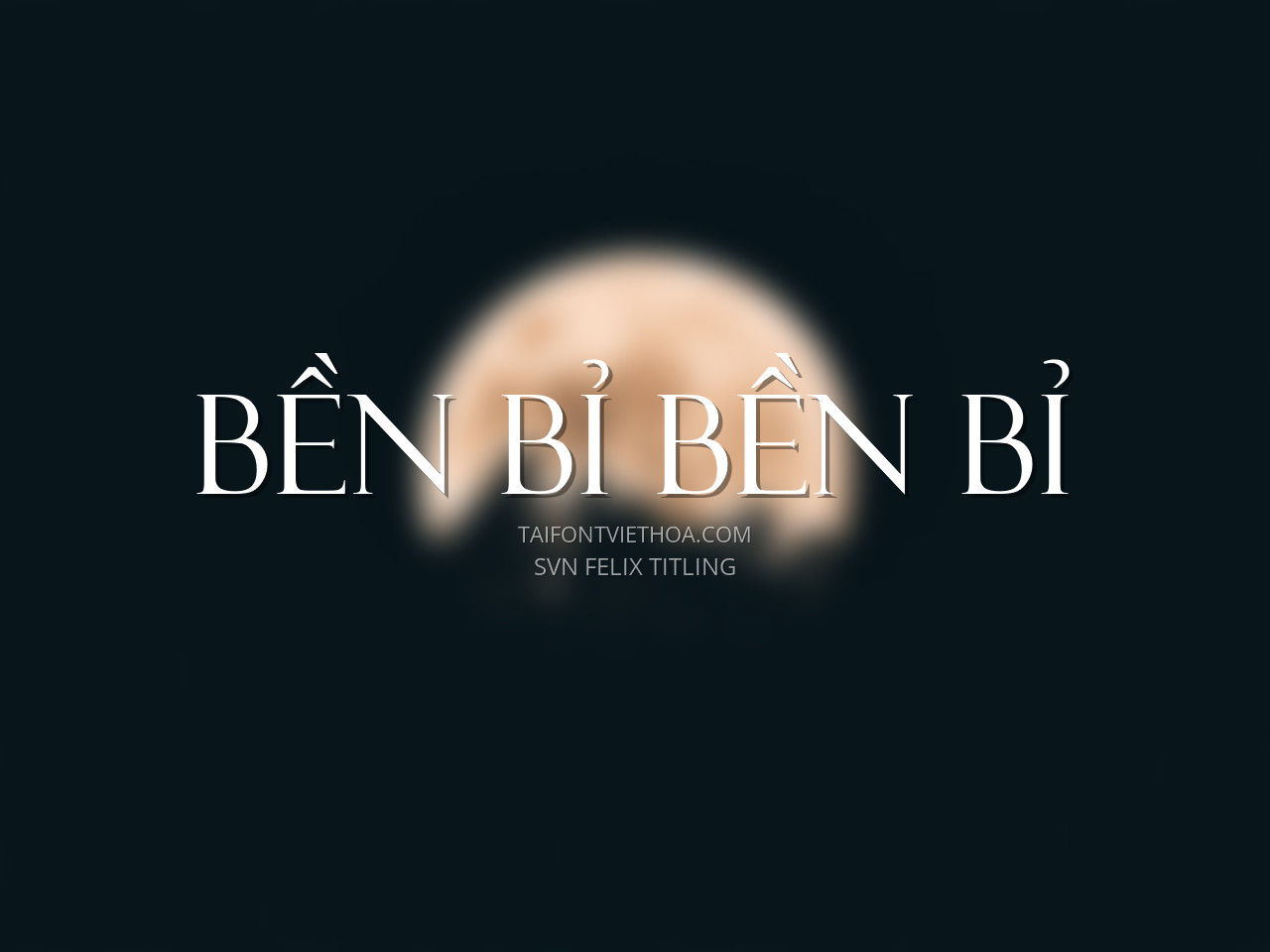
Font việt hóa SVN Felix Titling
Tác giả Font: Phillip Boydell
Giới thiệu về font SVN Felix Titling – Kiểu chữ serif in hoa cổ điển, trang trọng và sắc nét
SVN Felix Titling là phiên bản Việt hóa của font Felix Titling – một kiểu chữ serif chỉ bao gồm chữ in hoa với thiết kế cổ điển, thanh lịch và sắc nét. Font được tạo ra nhằm mang lại sự trang trọng và chuyên nghiệp, rất phù hợp cho các dự án thiết kế tiêu đề, logo, bảng hiệu và các ấn phẩm cao cấp.
Phiên bản Việt hóa của SVN Felix Titling đã được Taifontviethoa.comchỉnh sửa kỹ lưỡng, hỗ trợ đầy đủ dấu tiếng Việt và hơn 70 ngôn ngữ khác. Font giúp các nhà thiết kế dễ dàng áp dụng trong các dự án đa dạng mà vẫn giữ được vẻ đẹp cổ điển và sang trọng.
Thiết kế serif in hoa – Ứng dụng rộng rãi trong thương hiệu và bảng hiệu
SVN Felix Titling sở hữu các nét chữ in hoa sắc nét, cân đối và có độ tương phản cao, tạo cảm giác trang trọng và nổi bật. Font rất phù hợp cho tiêu đề, bảng hiệu, logo và các sản phẩm truyền thông cần sự ấn tượng và chuyên nghiệp. Phong cách thiết kế của Felix Titling rất thích hợp với các dự án thời trang, nghệ thuật và thương hiệu cao cấp.
Ứng dụng lý tưởng: thiết kế bảng hiệu, tiêu đề, logo thương hiệu, brochure, thư mời và các ấn phẩm quảng cáo sang trọng. Ngành nghề phù hợp: thời trang, mỹ phẩm, nội thất, giáo dục, nghệ thuật và các thương hiệu định vị theo phong cách cổ điển, trang trọng.